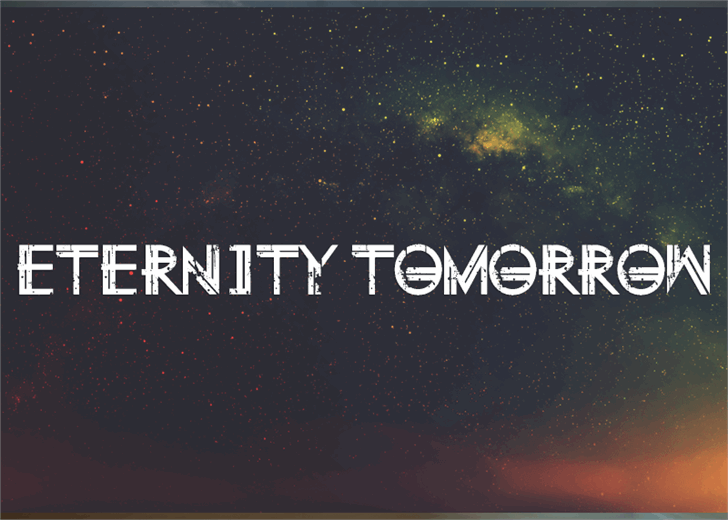
A fonte Eternity Tomorrow é perfeita para uma tipografia display moderna e vibrante. Inspirada na evolução contínua e no futuro promissor, a Eternity Tomorrow oferece linhas afiadas e cores vivas que capturam o espírito de inovação e projeção do século XXI. Seu designer, Hamilton, utilizou suas experiências criativas para criar um conjunto de fontes com uma grande variedade de opções de tamanho e estilo. Essa fonte é ideal para aplicações em sites, logotipos e publicidade, tornando-a perfeita para se destacar na web ou em qualquer aplicação visual moderna que deseje ser notada. Visite nosso site para informações adicionais sobre a Eternity Tomorrow font.